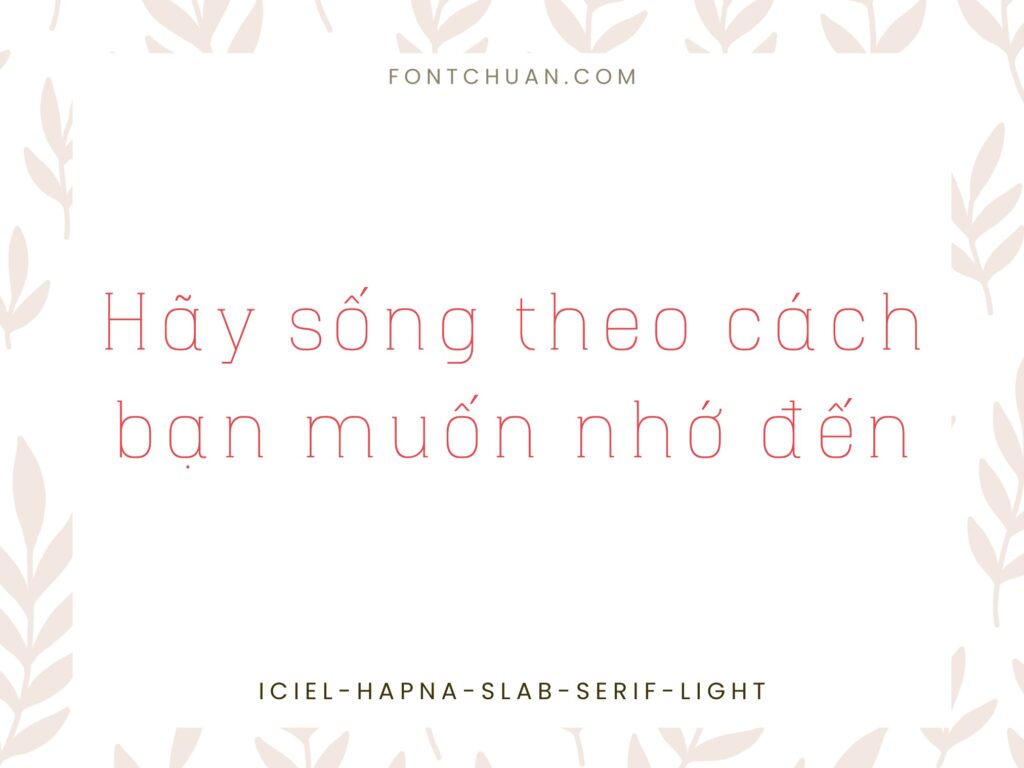
Font iCiel Hapna Slab Việt Hóa
Việt hóa bởi: Iciel
Hapna là một Font Slab Serif hình học độc đáo, được thiết kế bởi Mariya V. Pigoulevskaya và phát hành vào năm 2013. Lấy cảm hứng từ văn hóa bóng chày và ngôn ngữ đồ họa của những năm 1950, Hapna mang đến cảm giác cổ điển nhưng vẫn hiện đại. Bộ font bao gồm 6 trọng lượng khác nhau, với tổng cộng 406 ký tự và hỗ trợ các tính năng OpenType. Đặc biệt, phiên bản Hapna Slab Serif Light đã được Việt hóa bởi Iciel, hỗ trợ tiếng Việt cùng nhiều ngôn ngữ khác, đáp ứng nhu cầu đa dạng của người dùng. Thành viên của Font Chuẩn đã sưu tầm và chia sẻ font này, giúp cộng đồng thiết kế ứng dụng dễ dàng trong các dự án của mình.
Về đặc điểm thiết kế, Hapna sở hữu các đường nét chắc chắn và cấu trúc hình học rõ ràng, tạo nên sự cân đối và dễ đọc. Font này phù hợp cho các thiết kế như tiêu đề, poster, logo, bao bì sản phẩm và các ấn phẩm quảng cáo cần sự nổi bật và chuyên nghiệp. Ngoài ra, Hapna còn thích hợp cho các ngành nghề như quảng cáo, công nghệ, giáo dục và bất động sản, cùng các sự kiện đặc biệt như lễ hội, ngày Nhà giáo và sinh nhật.